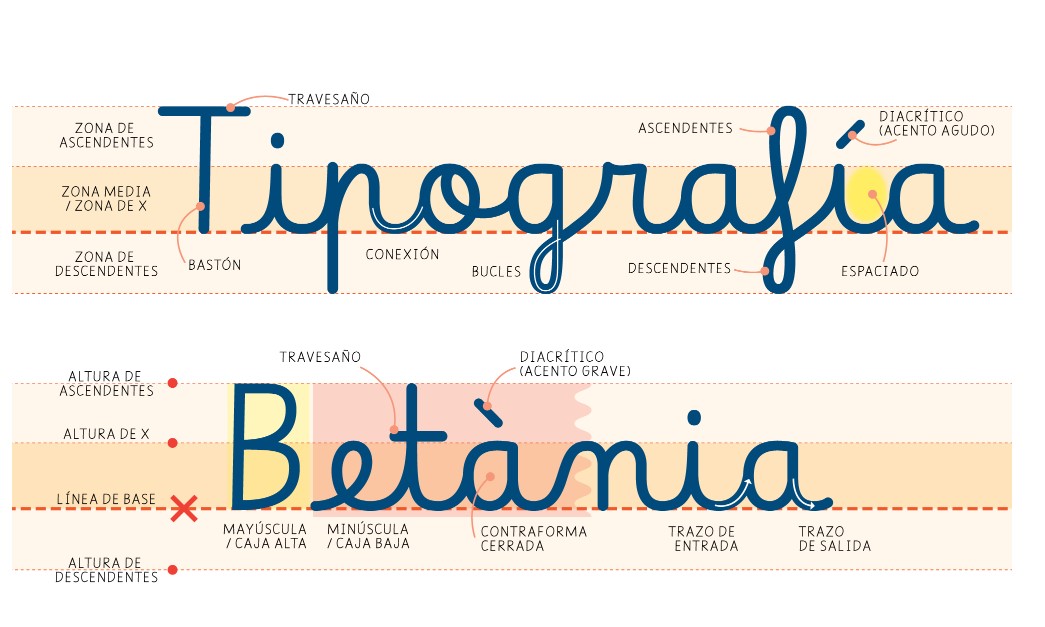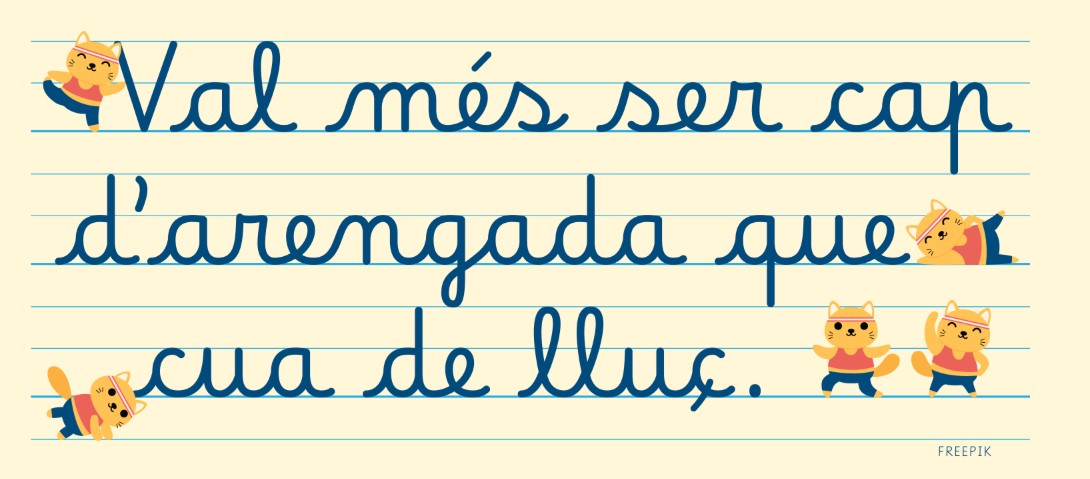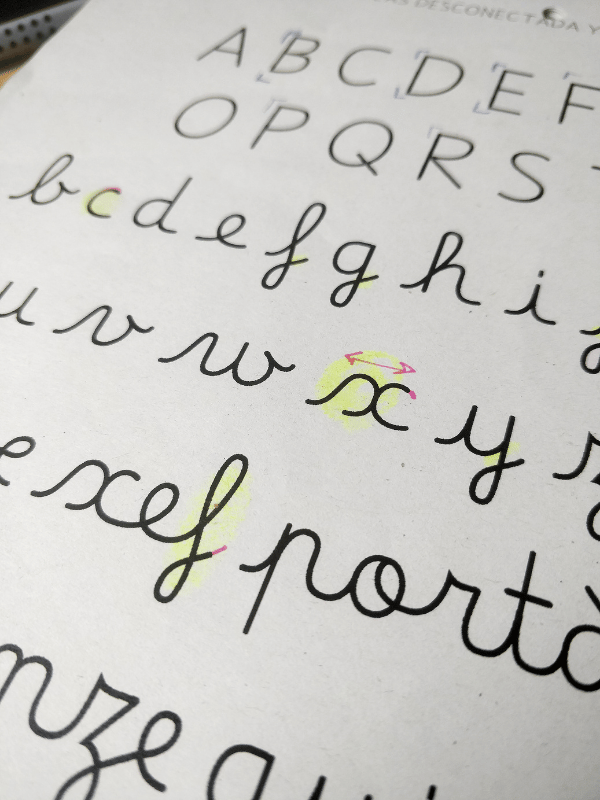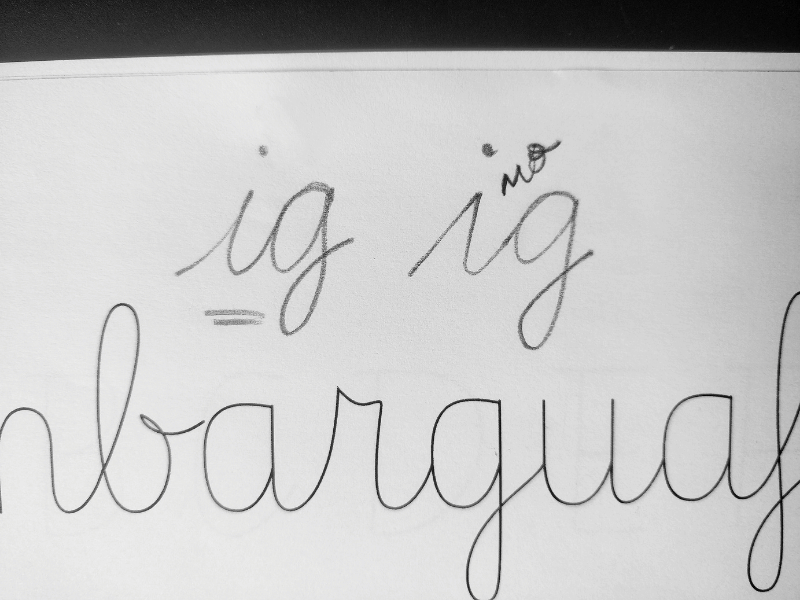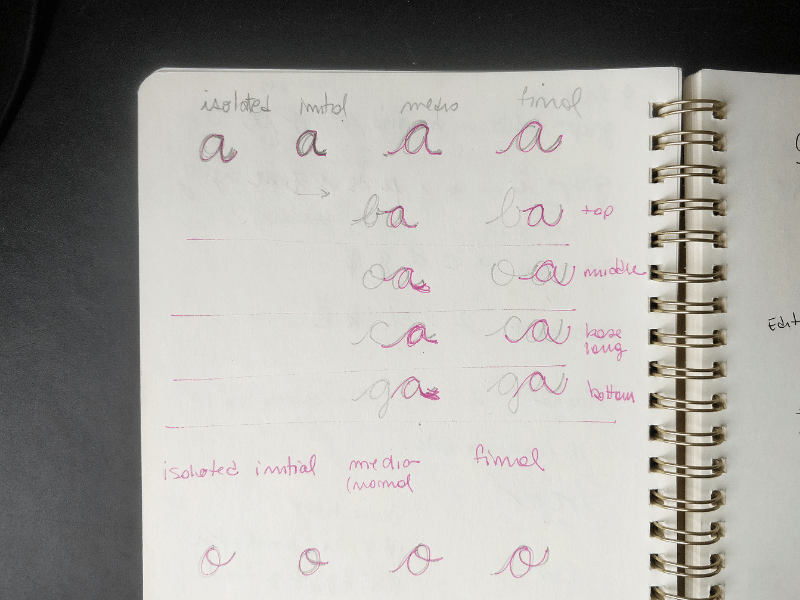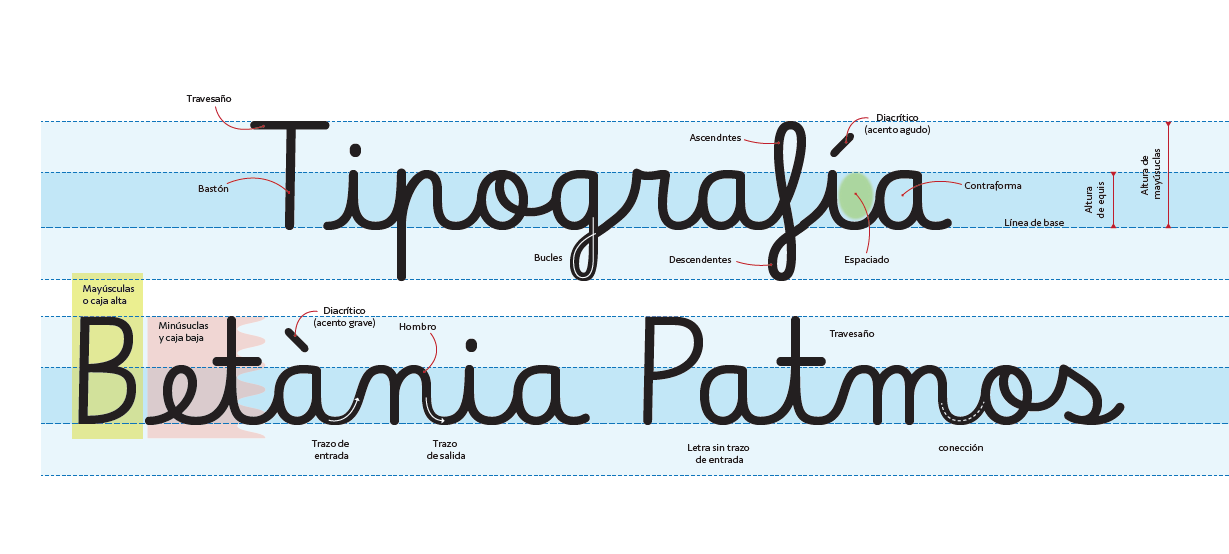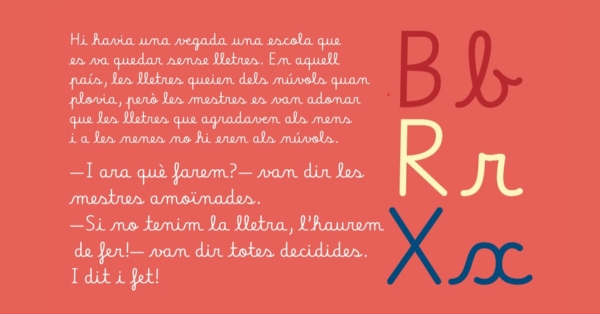
BetàniaPatmos, una lletra per infants de tot el món
Un grup de docents de l’Escola ha treballat amb especialistes en disseny per a la creació d’una tipografia d’ús públic en lletra lligada
L’escriptura manual que, com els sabers i la personalitat, evoluciona al llarg de la vida, és important perquè desenvolupa habilitats cognitives complexes com la memòria o el llenguatge i ajuda en la percepció visual de les lletres. És, a més, un procés ampli i dilatat que s’inicia abans de l’escolarització formal i que es va desplegant al llarg de tota la vida escolar, acadèmica i personal; una competència complexa que requereix moltes habilitats prèvies perquè es pugui aprendre de manera adequada.
No és, doncs, un procés espontani que es doni de forma natural: necessita un ensenyament i aprenentatge pacient que potenciï i estimuli l’alumne de forma orgànica per aconseguir que integri les habilitats necessàries per a la seva adquisició. L’objectiu principal és anar a buscar un grafisme funcional que sigui llegible, organitzat, ubicat en l’espai gràfic, proporcional i lligat de forma adequada.
A l’Escola BetàniaPatmos els infants s’inicien amb la pràctica de traços de preescriptura al llarg de l’etapa d’Infantil, pràctica que els ajudarà a adquirir habilitats motrius prèvies a l’escriptura mitjançant activitats on exerciten les espatlles, els avantbraços, els canells, les mans i els dits. Amb la motricitat fina fem propostes d’aprenentatge tals com, per exemple, enfilar, enroscar i desenroscar, modelar, tapar, cordar, arrugar, estripar…, habilitats que els facilitarà interioritzar la coordinació oculomanual perquè siguin més precisos en els primers traços.
D’una altra banda, a part de tenir en compte l’evolució madurativa que tenen els infants en el grafisme, mirem de treballar els traços rectes verticals o horitzontals, els traços en diagonal i els traços en formes corbes, des d’allò més simple fins a allò més complex, sempre ajudant i donant els recursos que necessitin per a aquesta pràctica.
Finalment, de forma natural, l’infant prova d’escriure en lletra de pal perquè és més accessible, fàcil i entenedora, i, a mesura que va creixent i adquireix més maduresa motriu, inicia el pas a la lletra lligada.
El debat sobre quina tipografia s’ha d’utilitzar a les aules és viu; el currículum del Departament d’Ensenyament deixa la majoria d’aquestes decisions en mans dels centres. A la nostra Escola fa ja un temps va sorgir la necessitat d’obrir un procés de reflexió entre els docents d’Infantil i Primària sobre la conveniència d’ordenar i revisar l’aprenentatge del grafisme, i és per això que un equip format per mestres de les dues etapes i una psicòloga de l’Escola es van documentar i es van formar per revisar, ordenar i escriure el procés d’ensenyament i aprenentatge d’aquesta habilitat. Fruit de la reflexió conjunta vam crear un document intern que defineix una línia d’escola i reforça la idea de l’aprenentatge de la lletra lligada.
Paral·lelament a aquest procés, l’any posterior a la pandèmia, el Patronat de la Fundació BetàniaPatmos va impulsar una acceleració en el procés de digitalització de l’Escola. L'any següent, el curs 2022-2023, vam iniciar la migració massiva dels documents de treball. La contractació de Google Workspace for Education Plus suposava la incorporació d’un entorn de treball segur que compleix amb la normativa europea pel que fa al Reglament General de Protecció de Dades i que posa a disposició dels seus usuaris eines que permeten construir coneixement de forma col·laborativa.
Però, com qualsevol canvi d’aquesta magnitud, aquest no estava exempt de problemes, i un dels més importants va ser descobrir que Google Fonts no disposava d’una lletra lligada pensada per a l’aprenentatge de l’escriptura dels infants. Aquest entrebanc impedia que tot el material didàctic elaborat pels equips de mestres d’Infantil i Primària es pogués utilitzar amb el nou entorn i amb les mateixes tipografies emprades fins aquell moment; el núvol no tenia les lletres que els nostres nens i nenes necessitaven.
Així doncs, ens trobàvem en una tessitura important: com mantenir el disseny i la creació de materials didàctics i poder desar-lo al núvol sense perdre el format? Donem preferència a la decisió pedagògica de continuar treballant amb lletra lligada o ens adaptem nosaltres a les tipografies existents? La resposta va ser clara: «Si no tenim les lletres, les haurem de fer».
Després de valorar moltes opcions, la direcció de l’Escola va donar suport a la necessitat de l’equip, donant via lliure per crear una nova tipografia que permetés continuar treballant com sempre s'havia fet, amb lletra lligada. I aquí començà un camí nou per a nosaltres, la creació d’una font nova que Google hauria de validar i que estaria disponible per a totes les persones del món que volguessin fer-ne ús.
De la mà dels especialistes en disseny de tipografies Carolina Giovagnoli i Juan Pablo del Peral, de l’empresa Huerta Tipográfica, vam descobrim uns conceptes totalment nous per a nosaltres, un nou lèxic que ens iniciava i ens acostava a conceptes com la línia base, l’ascendent, el descendent, el cos, l’asta, la cua, etc., durant un any paraules aquestes d’ús freqüent per a nosaltres.
Ara, la tipografia BetàniaPatmos ja està disponible de manera gratuïta a Google Fonts perquè qualsevol persona, escola o entitat del món la pugui utilitzar. Només cal obrir un document de text al Drive i seleccionar l’opció “Més tipus de lletra”, escriure al buscador “Betania Patmos” i seleccionar la que més us interessi.
Confiem que tota la feina feta els darrers anys contribueixi a millorar el procés d’aprenentatge dels nostres infants i us animem a fer servir la tipografia BetàniaPatmos!